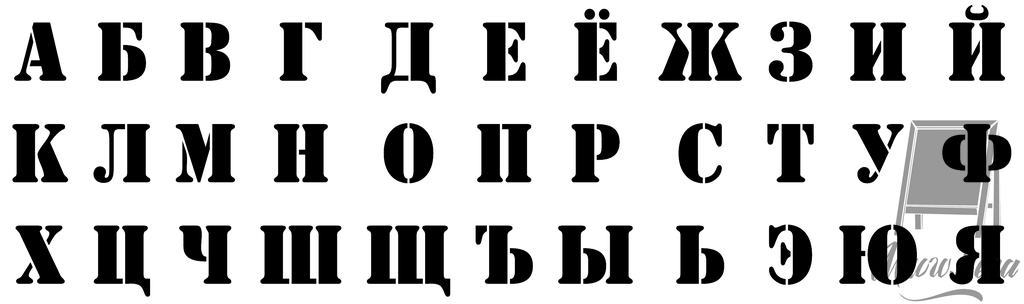
Все кириллические шрифты 2018 года
В 2018 году кириллических шрифтов вышло в несколько раз больше, чем год назад — поэтому мы решили рассказать только о тех, которые привлекли наше внимание (не обязательно в положительном смысле). Мы отобрали 185 шрифтов вместе с редакцией журнала «Шрифт».
Как обычно, мы разложили их по полочкам, пользуясь исключительно собственными предпочтениями и представлениями о прекрасном.
наши любимые шрифты;
шрифты с идеальной кириллицей;
шрифты с хорошим или приемлемым качеством кириллицы;
шрифты с кириллицей, вызывающей вопросы;
шрифты в которых кириллица не получилась совсем.
Мы рекомендуем пользоваться шрифтами из двух последних групп с большой осторожностью.
Но напоминаем, что не существует абсолютно плохих шрифтов: даже самый «ужасный» шрифт в определённой ситуации может идеально выполнить задачу и оказаться лучше, чем самый «прекрасный».
Отдельно, в начале списка, мы разместили список шрифтов, кириллицу к которым разработали мы сами. Как нам кажется, в итоге получилась достаточно полная картина кириллических новинок прошедшего года.
Шрифты разработанные или кириллизованные в студии CSTM Fonts
Styrene A by Berton Hasebe (Commercial Type), Cyrillic by Ilya Ruderman (CSTM Fonts) Styrene B by Berton Hasebe (Commercial Type), Cyrillic by Ilya Ruderman (CSTM Fonts) CSTM Xprmntl 02 by Yury Ostromentsky (CSTM Fonts)
Наши любимые шрифты 2018 года
Alterego by Pieter van Rosmalen (bold-monday) Arnold by Philipp Rebekka Neumeyer Rainer by Philipp Rebekka Neumeyer CoFo Chimera by Contrast Foundry IBM Plex Sans by IBM, Bold Monday IBM Plex Mono by IBM, Bold Monday IBM Plex Serif by IBM, Bold Monday ![Steinbeck-by-Roman-Gornitsky] Steinbeck by Roman Gornitsky
Zangezi by Daria PetrovaШрифты с идеальной, по нашему мнению, кириллицей
31Dec by Valery Golyzhenkov (Letterhead Studio) Baker Street 221B Mr Holmes by Yuri Gordon (Letterhead Studio) Darco X by Valery Golyzhenkov (Letterhead Studio) Libellula by Valery Golyzhenkov (Letterhead Studio) Mandelshtam Life by Yuri Gordon (Letterhead Studio) Mandelshtam Poetry by Yuri Gordon (Letterhead Studio) Pepperscreen by Valery Golyzhenkov (Letterhead Studio) Vogue Highline Sans by Yuri Gordon (Letterhead Studio) Vogue Highline Serif by Yuri Gordon (Letterhead Studio) WF Regular by Yuri Gordon (Letterhead Studio) WF Sans by Yuri Gordon (Letterhead Studio)
CoFo Sans by Contrast Foundry CoFo Robert by Contrast Foundry
November Slab by Peter Biľak November Stencil by Peter Biľak William Text by Maria Doreuli
Arbat PT by ParaType
Azo Sans 2 by Rui Abreu Baton Turbo by Anton Koovit & Yassin Baggar Bitum by Gayaneh Bagdasaryan & Vyacheslav Kirilenko Heron by Cyrus Highsmith (Occupant Fonts) Lab Grotesque Mono by Göran Söderström (Stockholm Design Lab) Zangezi by Daria Petrova
Шрифты с хорошим или приемлемым качеством кириллицы
DIN Next Decorative by Akira Kobayashi (Monotype) DIN Next Shapes by Akira Kobayashi (Monotype) Seol Sans by Adrian Frutiger (Monotype) Terry Junior by Terrance Weinzierl (Monotype) VAG Rounded Next by Tom Grace (Monotype)
Clother by Julie Soudanne, Ilya Naumoff, Jérémie Hornus Elowen by Katsia Jazwinska Felora by Dmitrii Chirkov
Lorna by Zakhar Yaschin (FontaZY) Monogamma by Tolya Doodko Morpha by Elena Kowalski (Glen Jan) NCT Torin by Nathan Zimet (NCT) Sinews Sans Pro by Jakob Runge (TypeMates)Abrakadabra by Tolya Doodko Epos by Denis Serebryakov (Dzianis Serabrakou) Kelpie by Olga Umpeleva NCT Larkspur by Nathan Zimet (NCT) Object Sans by Alex Slobzheninov, Sofia Yasenkova (Pangram) Rolleston by Oleh Lishchuk (Pepper Type) Streetline by Dmitry Greshnev (Green Type) Stylish Marker by Pedro Teixeira Vin Slab Pro by Oleh Lishchuk (Mint Type) Waba by Lewis McGuffie Type
Corsair by Samarskaya & Partners Disruptor’s Script by Antonina Zhulkova (Piñata) Gentlemens Script by Antonina Zhulkova (Piñata) Insolenta by Andrey Kudryavtsev (AKTF) Luftayah by Anna Seslavinskaya (Popkern) Nightelf by Andrey Kudryavtsev (AKTF)
RF Dewi by Misha Panfilov (Russian Fonts) RF Tone by Misha Panfilov (Russian Fonts)
Contract by Ksenia Erulevich (Art.
Lebedev Studio) Departure by Ksenia Erulevich (Art. Lebedev Studio) Ivolga by Taisiya Lushenko (Art. Lebedev Studio) Lavanda by Ksenia Erulevich (Art. Lebedev Studio) NF64 by Konstantin Lukyanov (Art. Lebedev Studio) Vlas by Konstantin Lukyanov (Art. Lebedev Studio)
Colus by Stan Partalev (fontfabric) Gilam by Ivan Petrov & Plamen Motev (Fontfabric Type Foundry) Mont by Svet Simov (Fontfabric) Singel by Jacklina Jekova and Nikolay Petroussenko (Fontfabric Type Foundry)
Squad by Svet Simov & Svetlin Balezdrov (Fontfabric Type Foundry)Alquitran Pro by RodrigoTypo Ding by Andrey Kudryavtsev (RodrigoTypo) Tobi Greek Cyrillic by Andrey Kudryavtsev (RodrigoTypo)